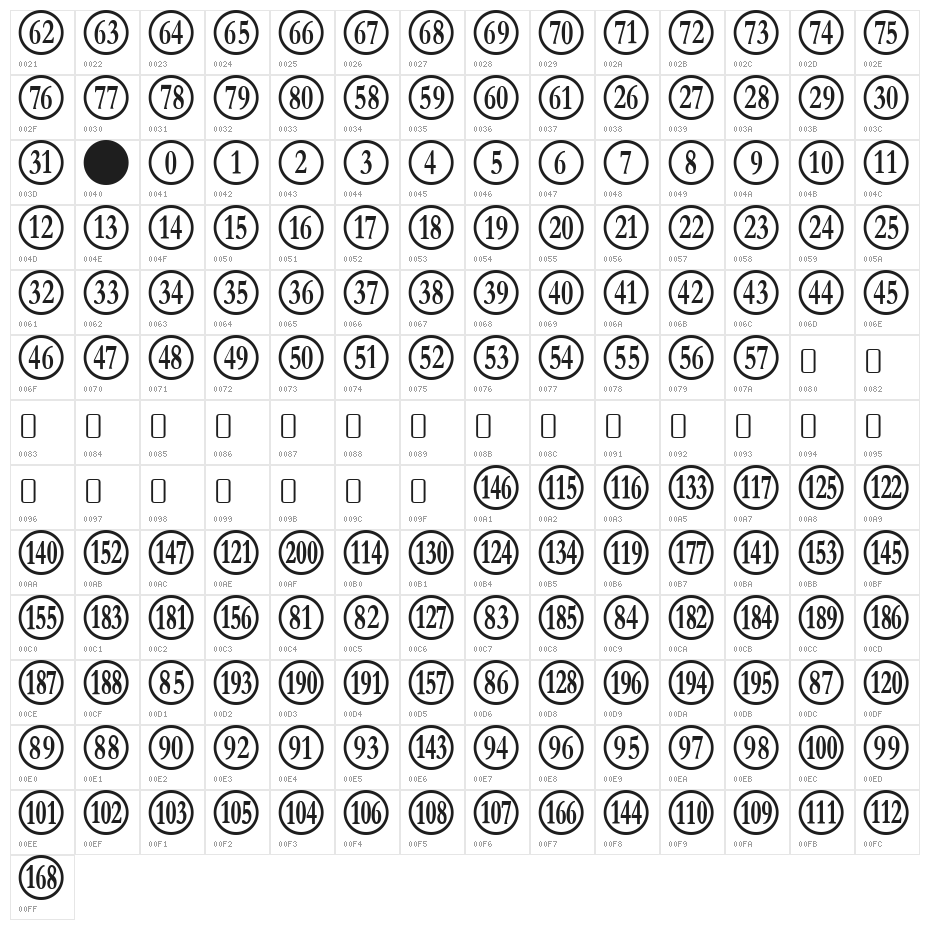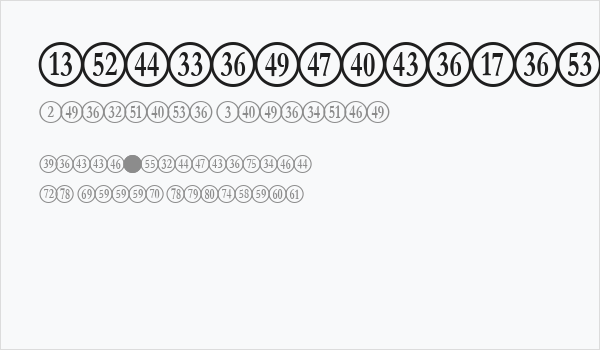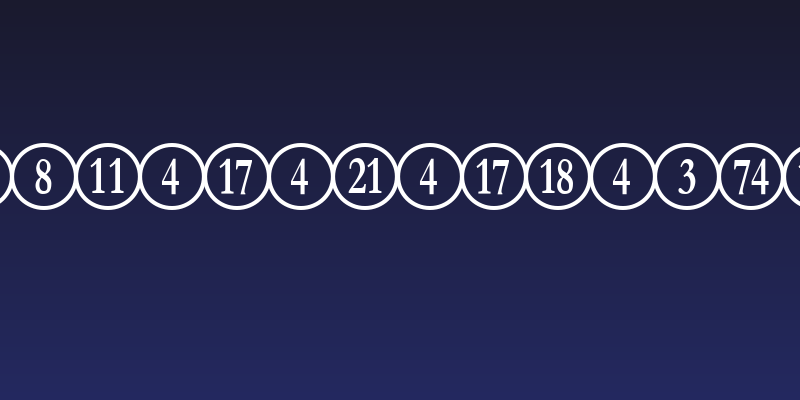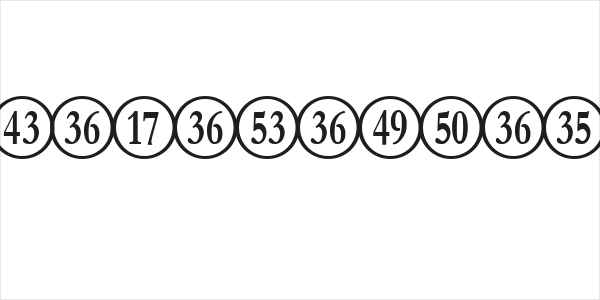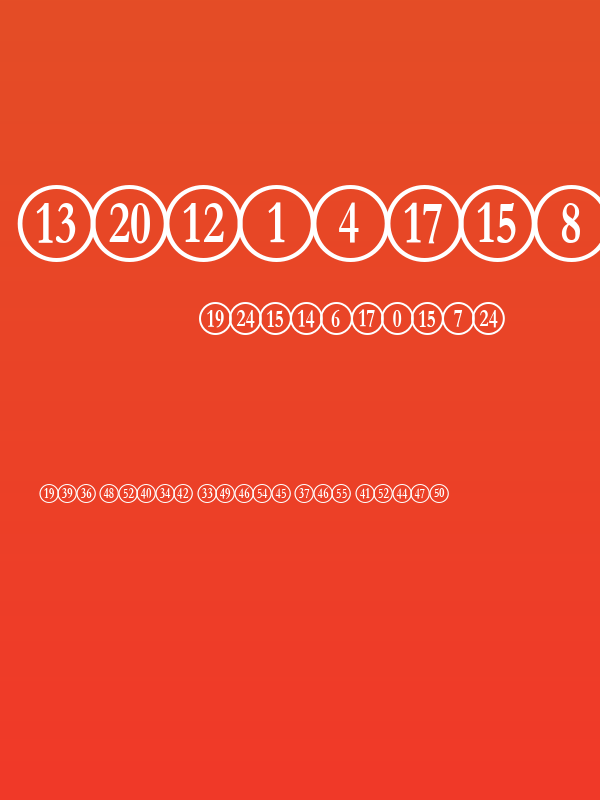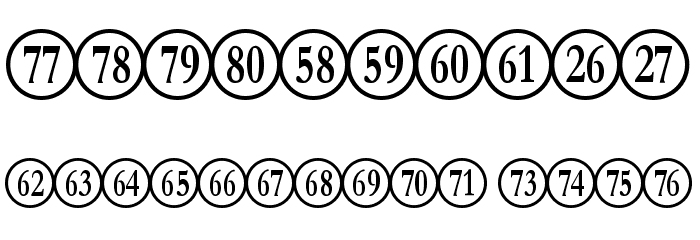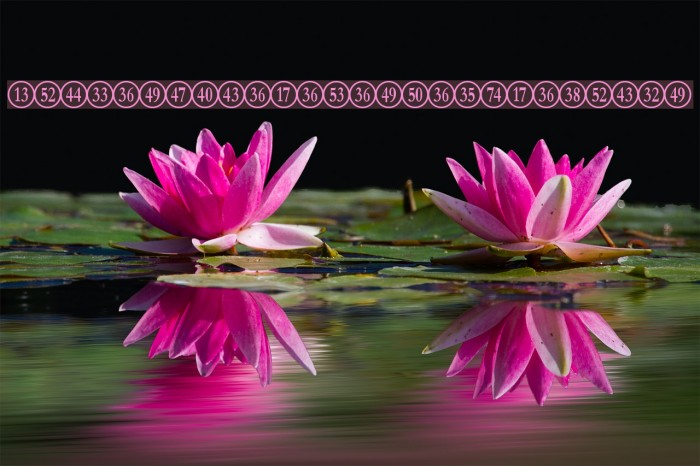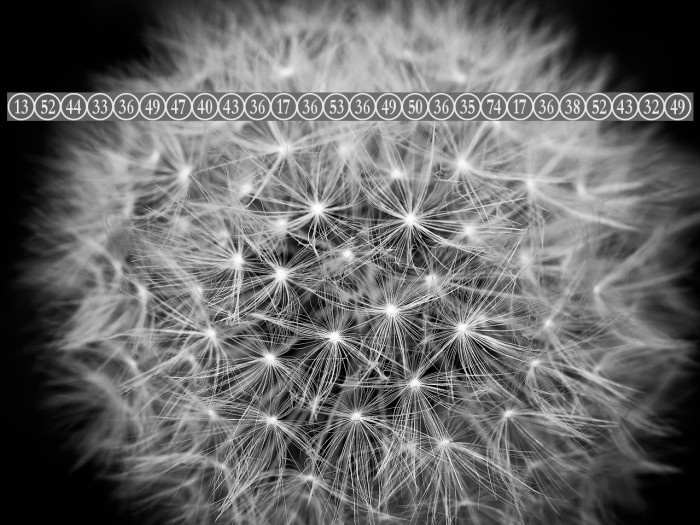
NumberpileReversed-Regular Font
| النمط العام | Playful, Modern |
| حالة الاستخدام | Logos, Educational materials, Games |
| مشاريع مقترحة | Ideal for educational materials, playful branding, games, or any design requiring a distinctive numerical display. |